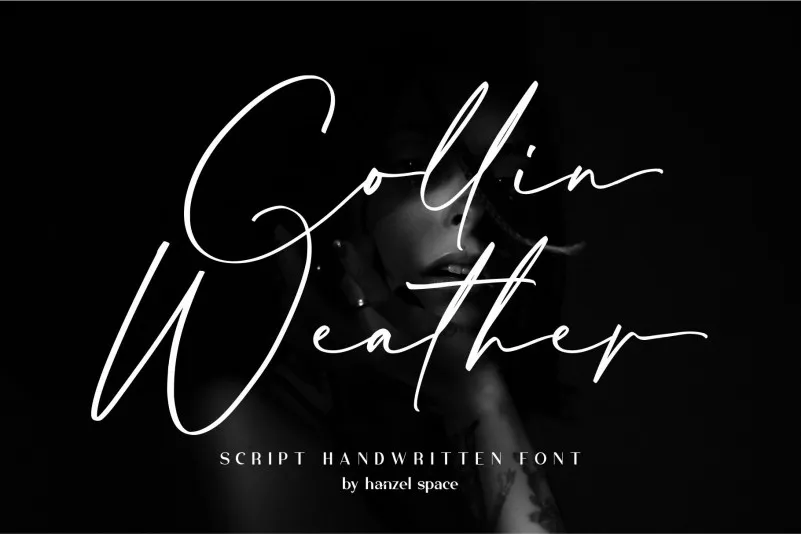
Collin Weather Font – Download Grátis
A fonte ‘Collin Weather Font’ é uma elegante tipografia script criada pela Hanzel Studio, com um toque casual chic que chama atenção por onde passa. Perfeita para criar rótulos de vinho, cartões de aniversário e convites de casamento, essa fonte tem a capacidade única de dar um toque sofisticado sem perder o toque pessoal. Com uma tipografia tão sofisticada, não é difícil imaginar suas letras sendo utilizadas em rótulos de vinhos exclusivos ou em cartões de aniversário criativos para celebrar grandes ocasiões. Além disso, sua versatilidade permite que a Collin Weather Font seja uma escolha ótima para criar um estandarte personalizado e moderno, fazendo-a ainda mais atraente para marcas e empresas. Se você está procurando por uma fonte de escrita perfeita para qualquer projeto que exija charme e estilo, sem perder aquela atmosfera descontraída da moda atual, então ‘Collin Weather Font’ é a escolha certa. Sem dúvida, ela será um grande aliado no seu próximo projeto criativo ou design gráfico.